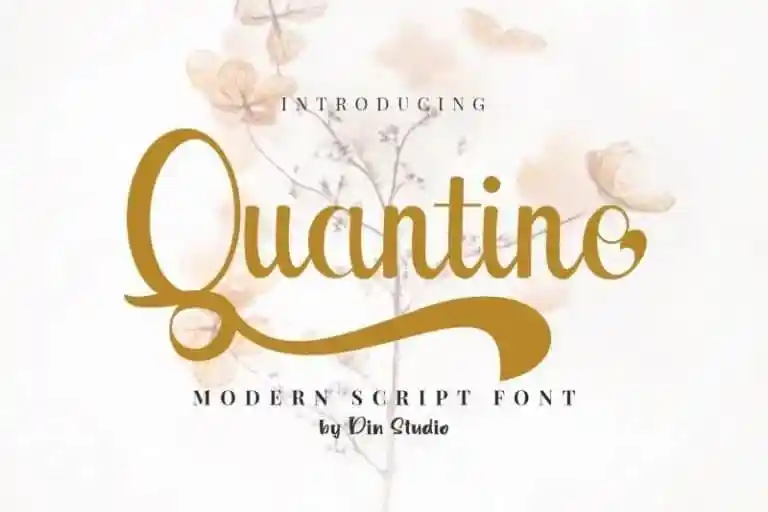
Quantine Script Font – Download Grátis
Quarantine Script Font é perfeito para qualquer designer criativo. Esta fonte feita à mão vai adicionar um toque natural belo a cada detalhe de seu design. É uma tipografia tipo letra moderna criada pela Din Studio com o melhor estilo, adequada tanto para exibição quanto para headlines, citações, logotipos, assinaturas e cartões de visita. Ideal também para necessidades como casamentos, decoração, festas, flores, e muito mais. Com sua elegância natural e modernidade refinada, a Quarantine Script Font é uma opção perfeita para quem procura um charme especial em seus projetos visuais.